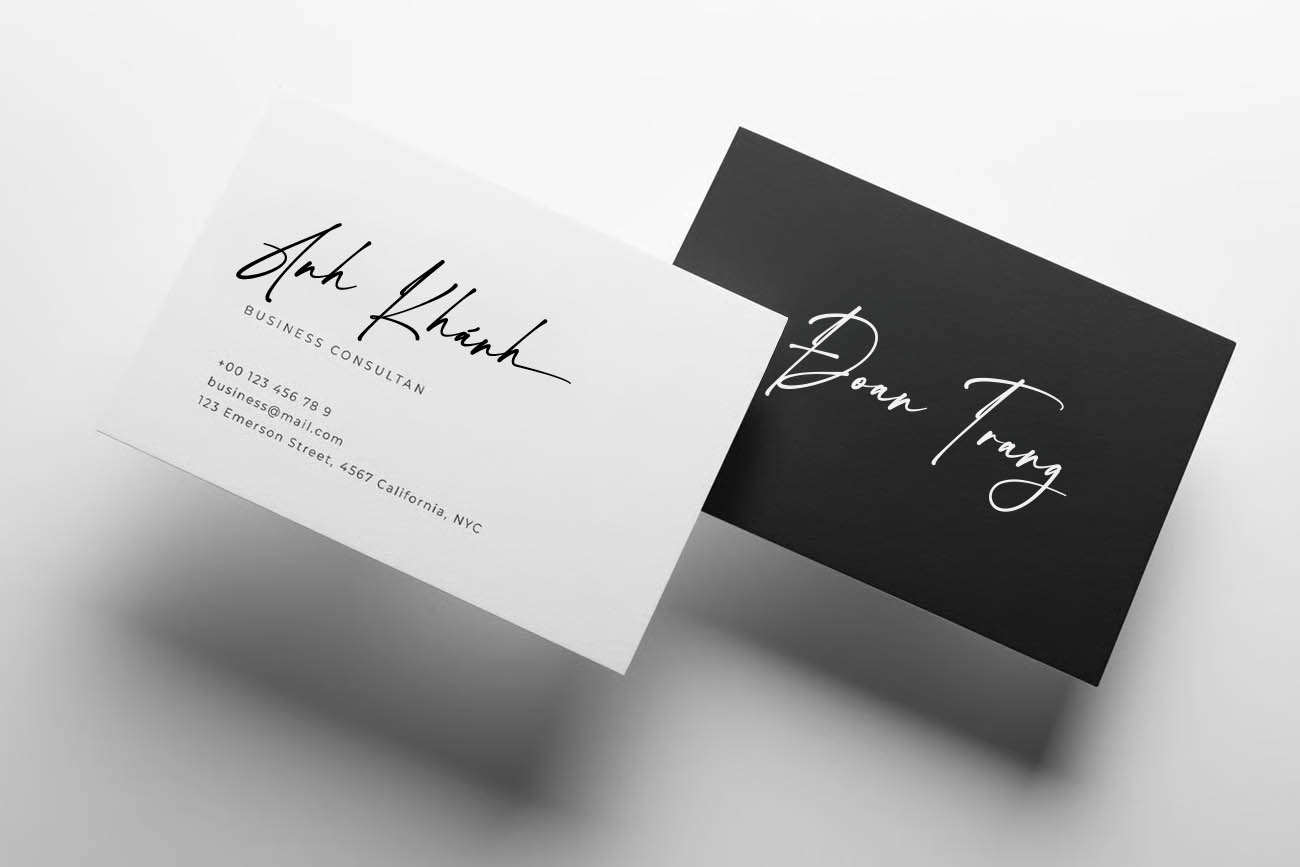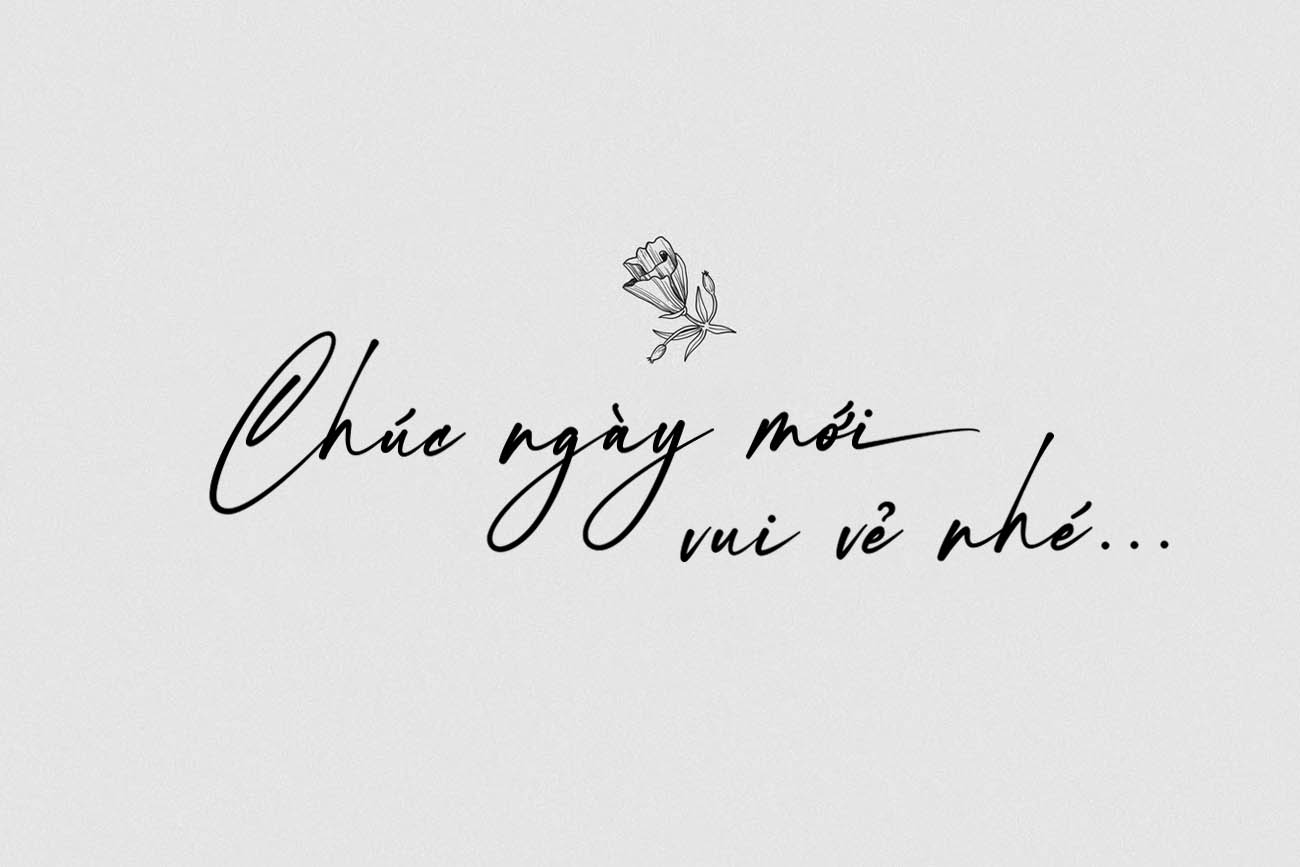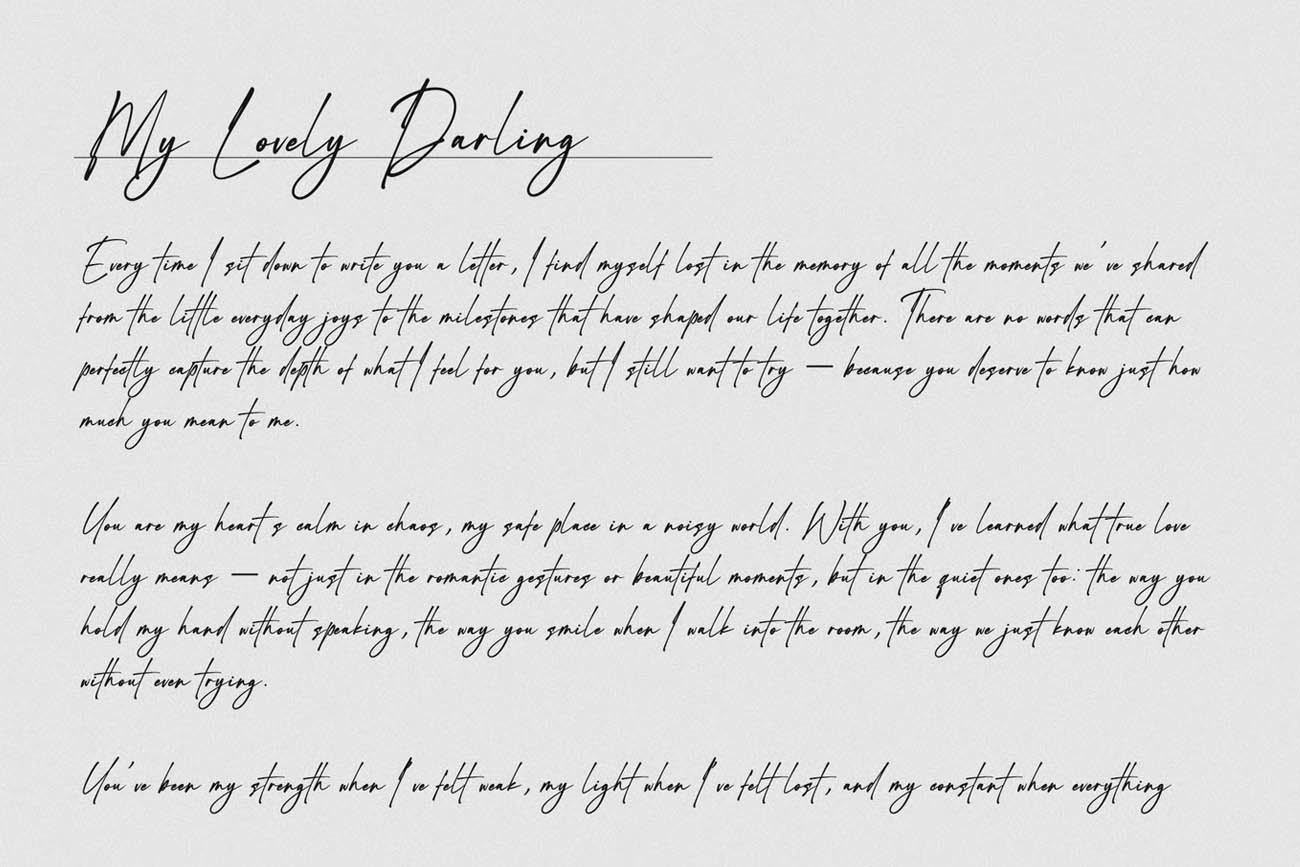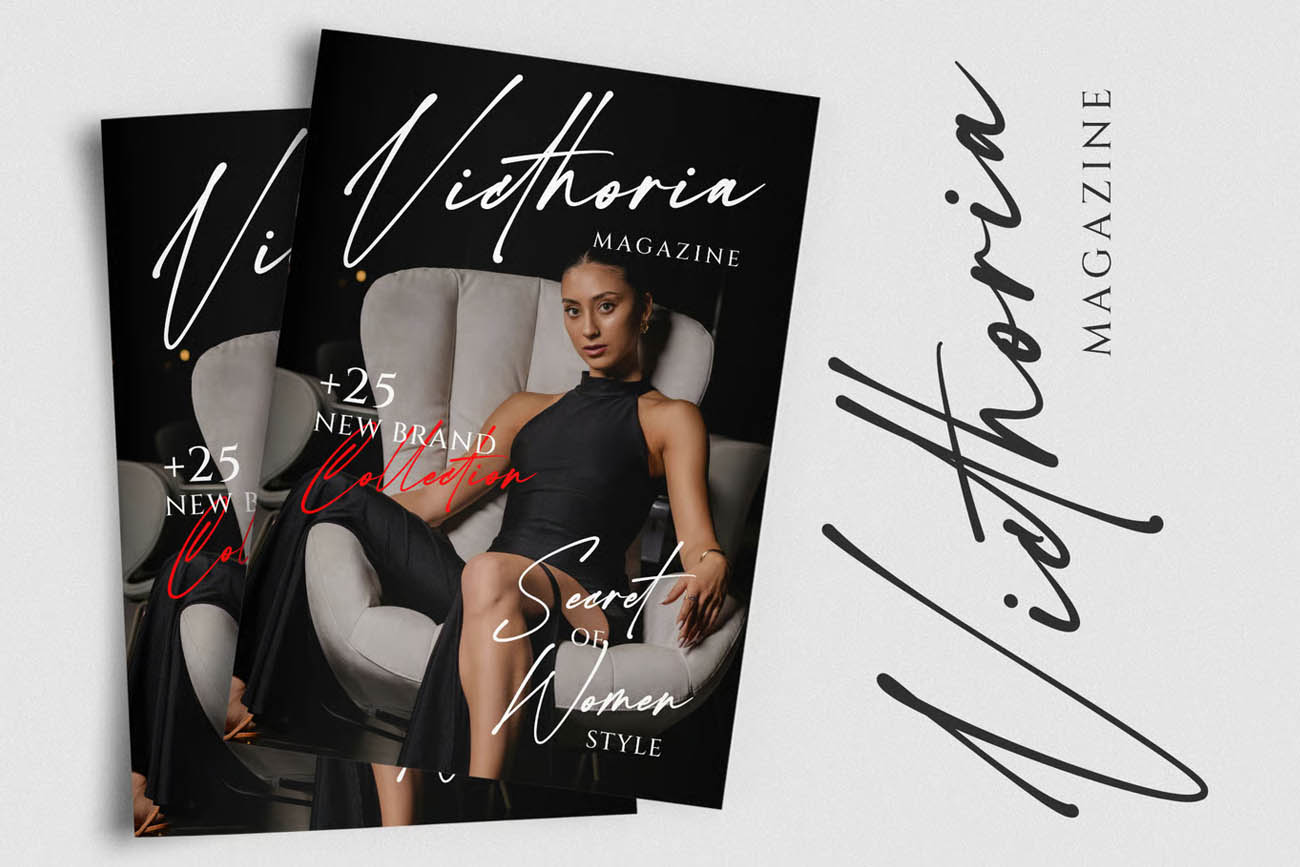
Bramostia là một font chữ ký tinh tế mang đậm dấu ấn cá nhân, được thiết kế bởi Rantautype Studio và Việt hóa trọn bộ bởi Phạm Sơn – Admin Fontdep.vn & S99.vn. Với phong cách font viết tay mềm mại, Bramostia mô phỏng nét mực tự nhiên của chữ ký tay – phù hợp cho các thiết kế sang trọng như logo thương hiệu cá nhân, thiệp mời cưới, watermark, tiêu đề blog.
Font sở hữu bộ ký tự đầy đủ hỗ trợ tiếng Việt, đi kèm các ligature tự động, ký tự thay thế (alternates) và kerning tinh chỉnh tỉ mỉ – giúp từng dòng chữ trông mượt mà, chuyên nghiệp và giàu cảm xúc hơn. Ngoài ra, Bramostia còn hỗ trợ hơn 200 ngôn ngữ khác nhau, tương thích tốt với các phần mềm như Photoshop, Illustrator, InDesign...
Nếu bạn đang tìm kiếm một font chữ ký Việt hóa đẹp mắt, mềm mại nhưng vẫn giữ nét thanh lịch, thì Bramostia là lựa chọn lý tưởng để thể hiện dấu ấn cá nhân độc đáo trong mọi dự án thiết kế.